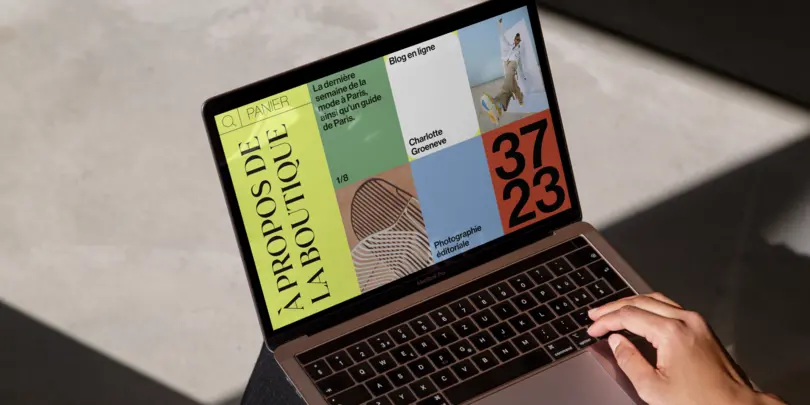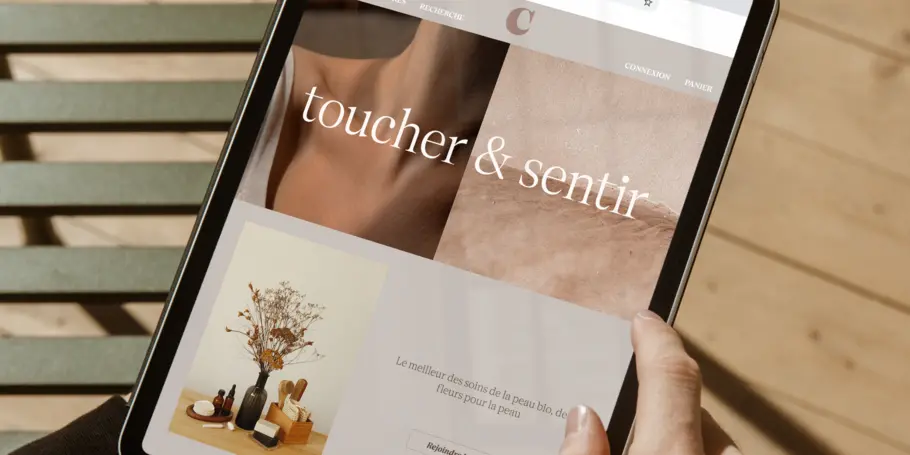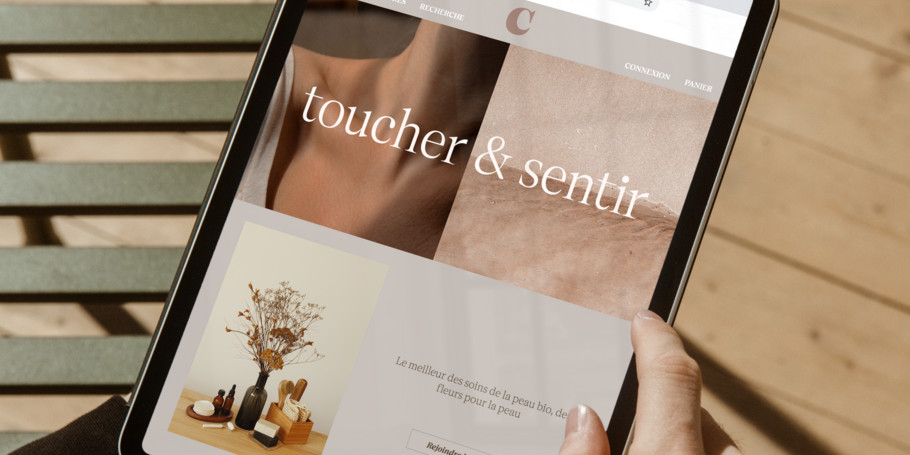
Comment la digitalisation impacte-t-elle la stratégie de marque ?
“ Choisissez une police de caractères qui correspond parfaitement aux valeurs et à l’éthique de votre marque, c’est ce qui aide vos clients à l’identifier et à se relier à elle. ”
Au cours des dix dernières années, la digitalisation généralisée a eu un impact considérable sur les créatifs. En termes de stratégie de marque, le storytelling a remplacé la vente. Il revient aux créatifs de raconter l’histoire et de faire évoluer l’expérience utilisateur.
Le temps où le marketing était fait de papier est loin. Aujourd’hui, l’histoire commence avec le numérique, au cœur du marketing digital. En 2021, on comptait 89% d’entreprises ayant adopté une stratégie commerciale digital-first ou prévoyant de le faire. 91% d’entre elles sont engagées dans une initiative digitale.
Si l’on imagine l’arc narratif du marketing de marque, le premier élément déclencheur est le progrès technologique. Mais la pandémie mondiale de la COVID-19 est ce qui a vraiment porté la numérisation à son climax. Distanciation sociale et confinement ont fait exploser le besoin en sites Web et autres vitrines numériques. De là, sont nées de nouvelles possibilités d’innovation et de créativité. Et aussi, quelques obstacles en cours de route.
Voici les principaux challenges en matière de branding dans un monde post-covid :
Humaniser votre marque et ses espaces numériques.
Pendant la pandémie, les consommateurs sont devenus plus conscients de ce que les marques véhiculent par leurs designs, leurs valeurs, leurs éthiques. Les marques se sont donc retrouvées confrontées à un nouveau défi, celui d’illustrer leur mission numériquement. Heureusement, les designers sont là pour les accompagner dans ce type d’évolution.
Parmi les dernières tendances dans le domaine du digital, les polices de caractères se sont imposées comme un élément essentiel des projets de branding. Choisir une police de caractères qui correspond parfaitement aux valeurs et à l’éthique de votre marque, c’est ce qui aide vos clients à l’identifier et à se relier à elle.
Être toujours disponible pour vos clients.
Les clients recherchent une grande capacité de communication et de serviabilité de la part des marques. Ils souhaitent que les marques soient réactives et qu’elles offrent la possibilité de faire des feedbacks par le biais des espaces numériques. Qu’il s’agisse d’une assistance par messagerie ou d’une ligne directe, les clients veulent avoir une voix et un véritable dialogue avec les marques avec lesquelles ils entrent en interaction.
Pour répondre à ces attentes des consommateurs, les marques doivent être joignables en permanence pour venir en aide à leurs clients. Lorsque vous sélectionnez vos éléments de branding, assurez-vous d’opter pour une typographie qui rend service, elle aussi. Parfaitement fonctionnelle et facile à lire, elle doit créer une communication aussi limpide que rapide avec vos clients. Et s’il y a bien un avantage que le design numérique a sur le design d’impression, c’est qu’il offre la possibilité d’effectuer les mises à jour plus facilement.
Avoir une portée mondiale et locale.
Avec la digitalisation des marques, l’audience du marketing de marque est plus internationale qu’avant. Cela signifie que les marketeurs du numérique doivent satisfaire une multitude de cultures et de langues pour atteindre leur marché mondial. Pour communiquer à si grande échelle, il est nécessaire d’adapter votre message au marché.
Au moment d’intégrer votre énoncé de mission sur votre site Web, soyez sûr qu’il entre en cohérence avec le design. Vous devrez transmettre vos valeurs et votre éthique de marque de manière universelle, grâce à des polices de caractères qui fonctionnent dans plusieurs langues et partout dans le monde. Croyez-le ou non, 95% du Web design repose sur la typographie. Intéressant à noter, quand on sait qu’une marque a moins de 50 millisecondes pour donner une bonne première impression.
Suivre les améliorations constantes.
Un autre challenge : suivre l’évolution continue des attentes des consommateurs. Dans un monde digital, de nouvelles technologies émergent sans cesse, les choses changent en permanence et les marques ont plutôt intérêt à suivre les dernières tendances. Pour rester dans la course, les entreprises peuvent avoir besoin d’engager un consultant en médias sociaux ou doivent apprendre à manier ces nouvelles technologies.
Pour 85% d’adultes, la version mobile du site Web d’une entreprise devrait être aussi efficace, voire meilleure, que la version pour ordinateur. Pour répondre à ces attentes, de nombreuses marques se sont également équipées d’une application mobile pour accompagner leur site Web. À mesure que de nouvelles mises à jour logicielles sont publiées, les applications doivent être entretenues pour rester fonctionnelles. En suivant ces améliorations constantes, votre entreprise préserve sa compétitivité.
Fidéliser.
Les polices de caractères jouent un rôle essentiel dans une bonne expérience utilisateur. Une fois que vous avez défini les valeurs fondamentales et la mission de votre marque, vous pouvez exploiter la typographie pour créer cette relation client durable. Choisissez une police de caractères qui correspond à la personnalité de votre marque et utilisez une iconographie qui résonne avec les consommateurs. Quelle que soit la mission de votre marque, la typographie est essentielle pour créer et entretenir votre relation avec le consommateur.